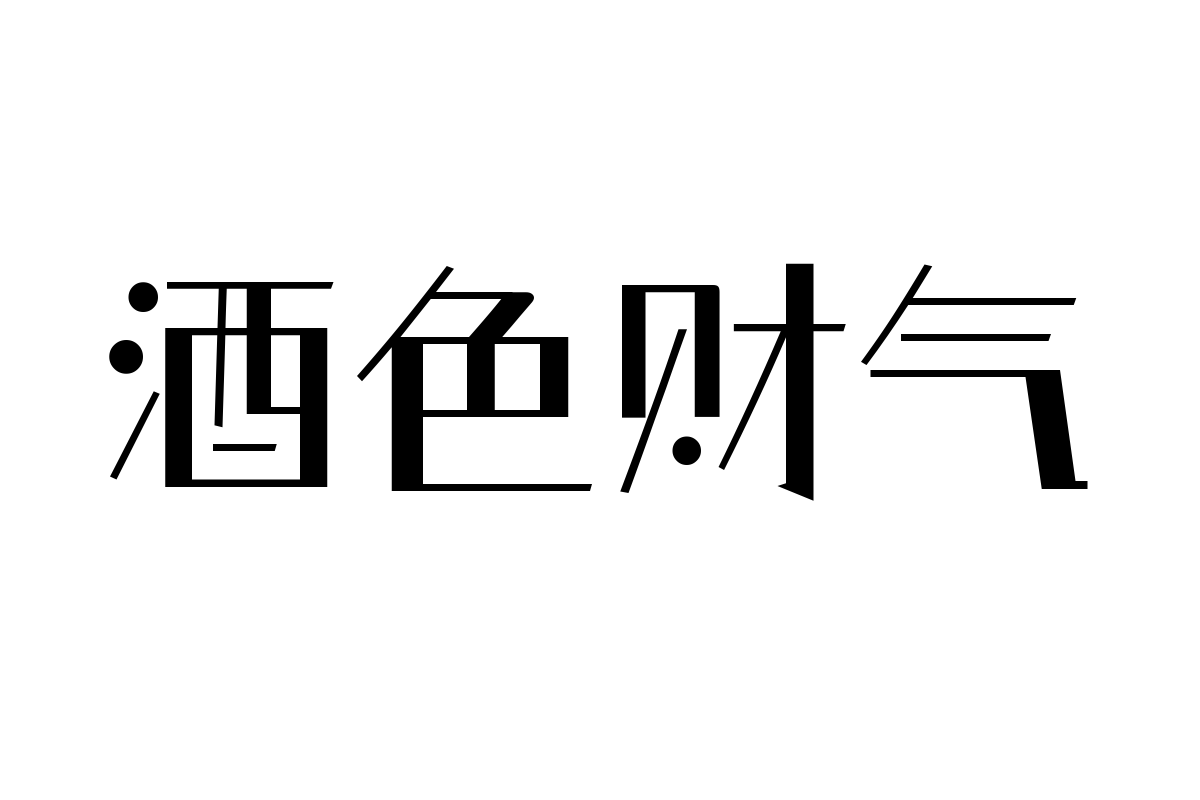
仓耳非白W03是一款由北京仓耳文字技术有限公司设计的免费商用字体。这款字体以其独特的风格和结构,为各种设计场景提供了丰富的选择。以下是对其特点的介绍:
1. **品牌背景**:仓耳字库是一家专注于屏幕显示字体、创新型正文字体和可变字体设计的字库公司。公司拥有自主专利的核心技术,在正文字体和屏显字体方面有深入研究。
2. **字体特性**:仓耳非白W03拥有5个字重,粗细对比明显,风格强烈。其结构方整,笔形简洁利落,带有区别于其他字体的风格。设计时,除了加粗笔形强调“黑”,也增加了部分细线强调“白”,字形转折处均做直角处理,撇捺同样以直线呈现。